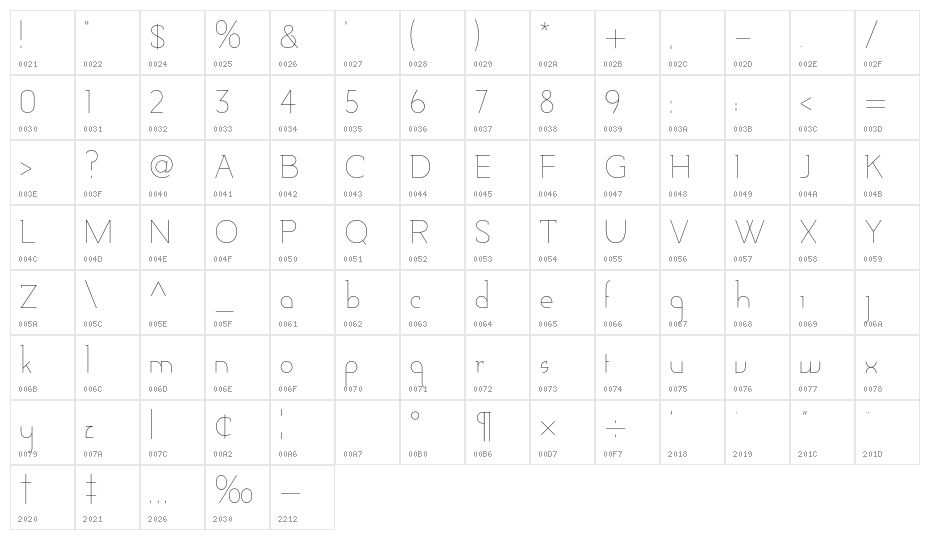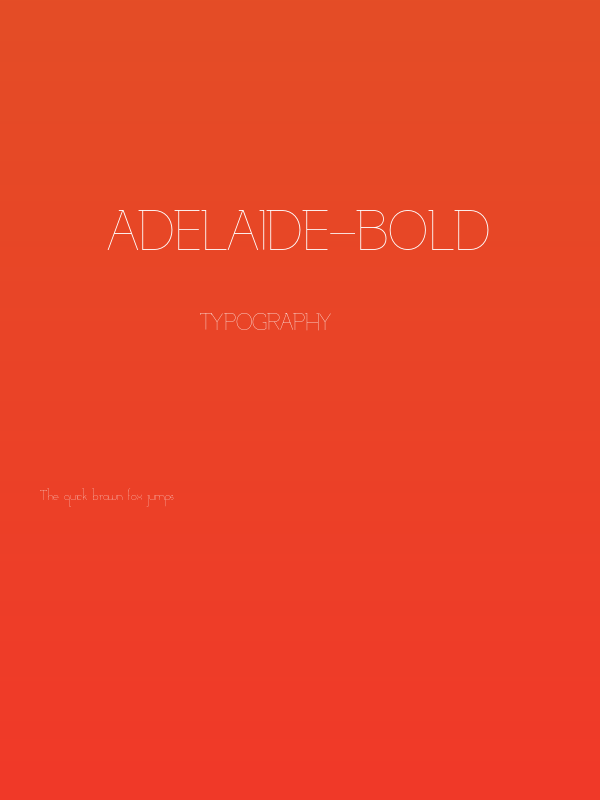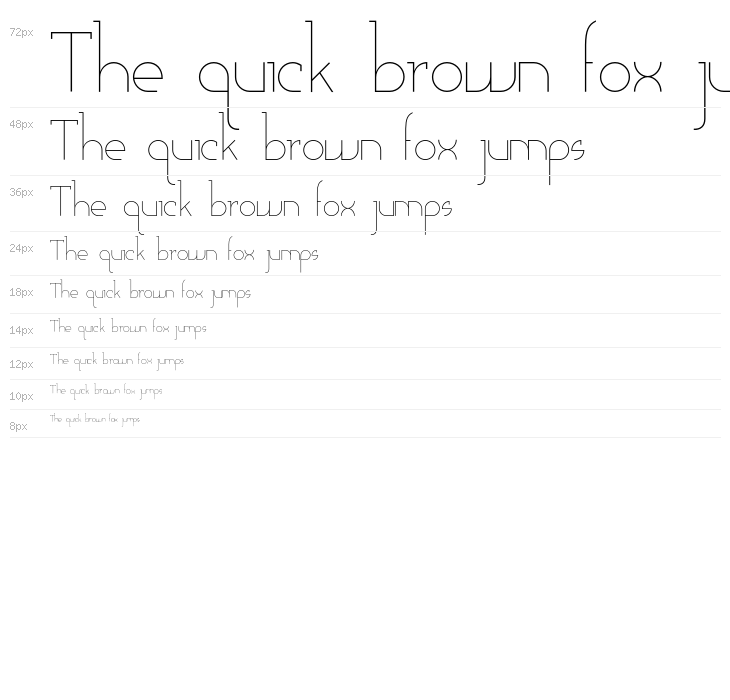
Adelaide-Bold Font
| Caso d'uso | Headlines, Logos, Digital interfaces |
| Progetti proposti | Ideal for modern branding, minimalist posters, editorial design, and digital interfaces. |